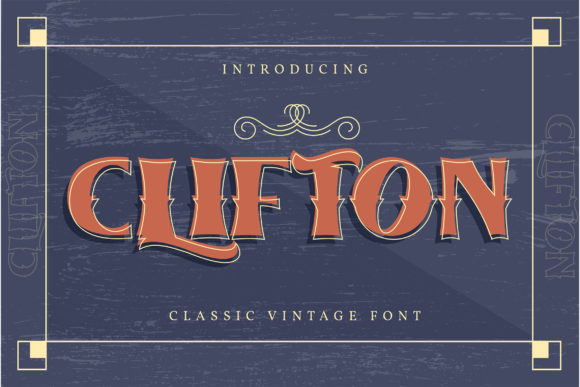
Clifton - это шрифт с черными буквами, вдохновленный винтажными знаками и этикетками в стиле ретро.
Это делает его идеальным выбором для создания уникальных дизайнов, таких как плакаты, логотипы, этикетки, упаковка и многое другое!